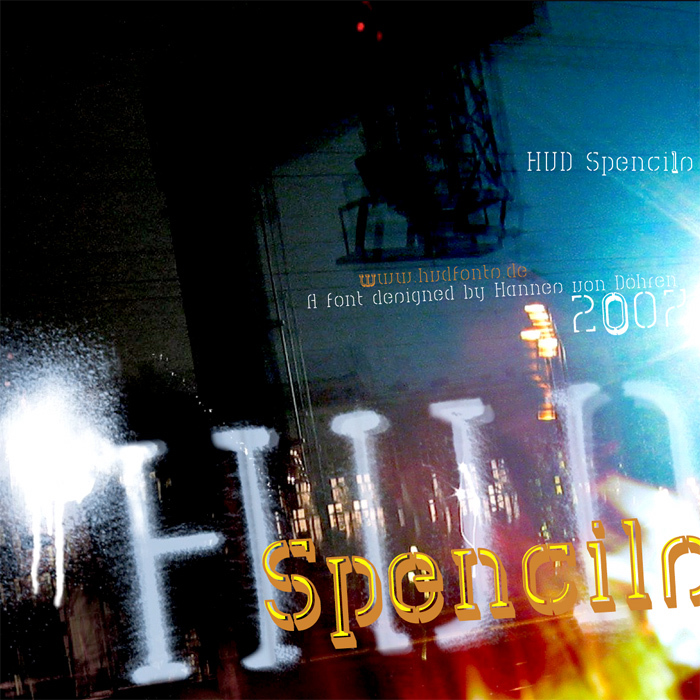
HVD Spencils Block di Hannes von Dohren è un carattere display gratuito in stile stencil retrò. Grazie alle lettere delineate e alla robusta ombra sfalsata, le maiuscole acquisiscono un aspetto tridimensionale, tipico delle insegne dipinte a mano. Le interruzioni ripetute e le curve smussate mantengono viva l'estetica stencil, mentre l'interno cavo e il marcato effetto ombra rendono il carattere incisivo, audace e leggermente industriale.
È l'ideale per titoli di locandine, grafiche per vetrine, packaging, copertine di album e volantini, dove un font gratuito dotato di tale profondità è in grado di reggere il titolo senza bisogno di ulteriori interventi. Usalo per titoli brevi, monogrammi o copertine quando vuoi che siano le lettere stesse a evocare il fascino vintage di un vecchio emporio.